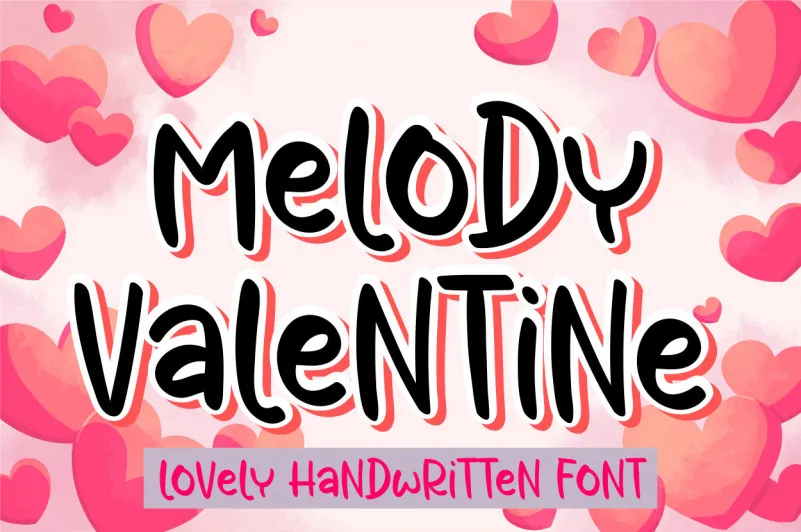
Melody Valentine Font – Download Grátis
Esta é uma fonte de exibição simples e interessante com um tom agradável que torna esta fonte extremamente versátil. Seu encanto amigável permite usos em diversos contextos, desde cartões de agradecimento até cartazes de logotipos ou design empresarial. Ela deslumbra nas mensagens pessoais e nos elementos visuais de alta qualidade. Melody Valentine é perfeitamente adaptada para estilos criativos, destacando seus projetos com um toque único. Acesse o seu projeto visual e descubra como ela pode revolucionar sua criação!
Designer: sugiharto1790